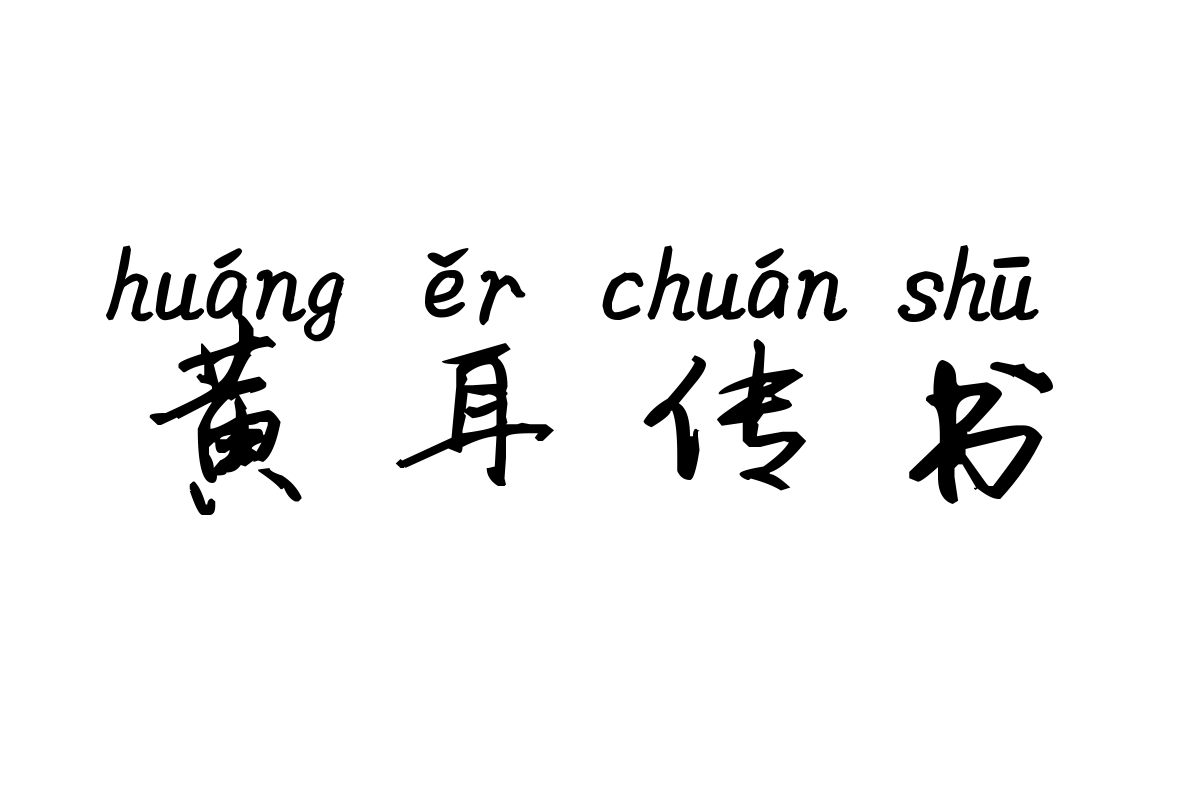
米开酒醉的蝴蝶是一种字体,由著名设计师米开设计。这种字体的特点是字形独特,线条流畅,给人一种优雅的感觉。字体中的蝴蝶形象,仿佛在酒醉中翩翩起舞,充满了艺术感和浪漫气息。
字体的笔画粗细适中,既有力量感,又不失柔和,非常适合用于标题、正文等文字。同时,字体的间距和行距也经过精心设计,使得整个文本看起来既紧凑又富有节奏感。
总的来说,米开酒醉的蝴蝶是一种非常独特且具有艺术感的字体,适合用于需要表达个性和创意的设计作品中。